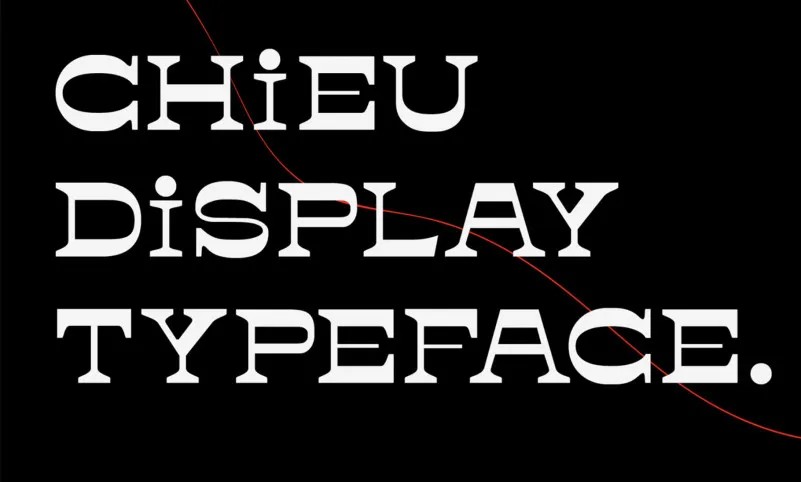
Agradecemos por olhar a Fonte Chieu Display. “Chieu” (chiêu) é uma palavra antiga do vietnamita que significa “esquerda”, simbolizando figurativamente a ideia de “contra a multidão”. A Chieu Typeface é um tipo customizado com contraste reverso, criado para indivíduos criativos e autênticos que desejam experimentar fontes únicas e diferentes. Esta fonte se destaca pela sua personalidade marcante, oferecendo uma aposta no design único, ideal para aqueles que buscam expressar-se de maneira única em suas criações digitais.